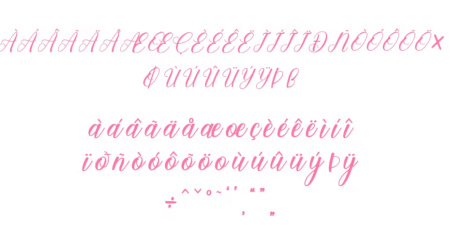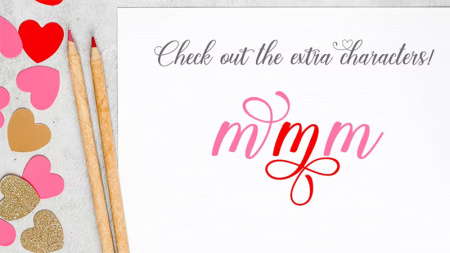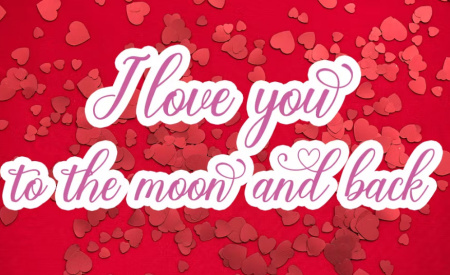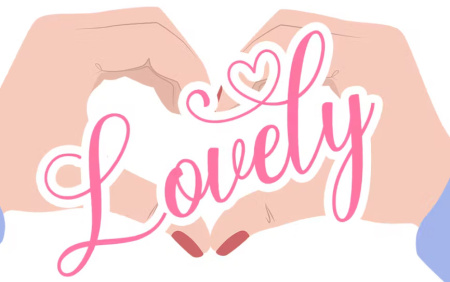
فونت انگلیسی قلبی Wonderful Love که ازسایت جی اف ایکس دانلود در اختیار شما عزیران قرار گرفته شده است یک فونت انگلیسی قلبی زیبا برای انواع طراحی ها می باشد. برای دانلود فونت انگلیسی قلبی و مشاهده پیش نمایش آن به ادامه مطلب مراجعه کنید.
فونت انگلیسی Angelist طرح قلب آپدیت 2023
دانلود فونت انگلیسی طرح قلب با نام Angelist در جی اف ایکس دانلود. این فونت زیبای قلبی به صورت آپدیت به مطلب اضافه شده است شما می توانید برای طراحی پروژه های برندسازی، آرم ها، بروشورها، کارت های ویزیت، دعوت نامه های عروسی و سایر موارد دیگر از این فونت استفاده نمایید. در ادامه می توانید نمونه عکس ها را مشاهده و فایل اصلی را با خرید اشتراک یا تک فایل دانلود نمایید.